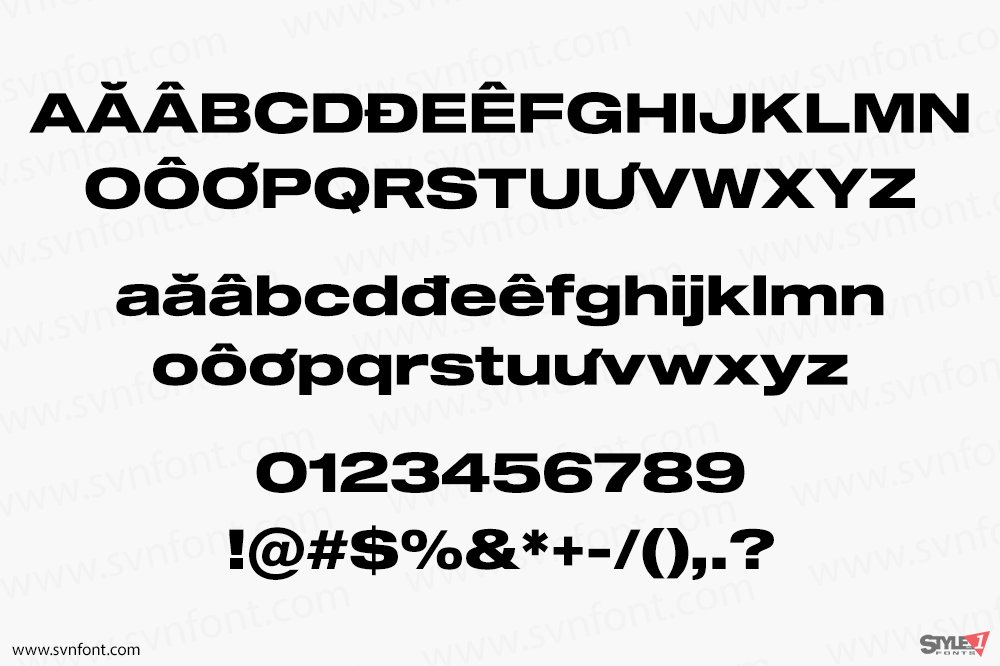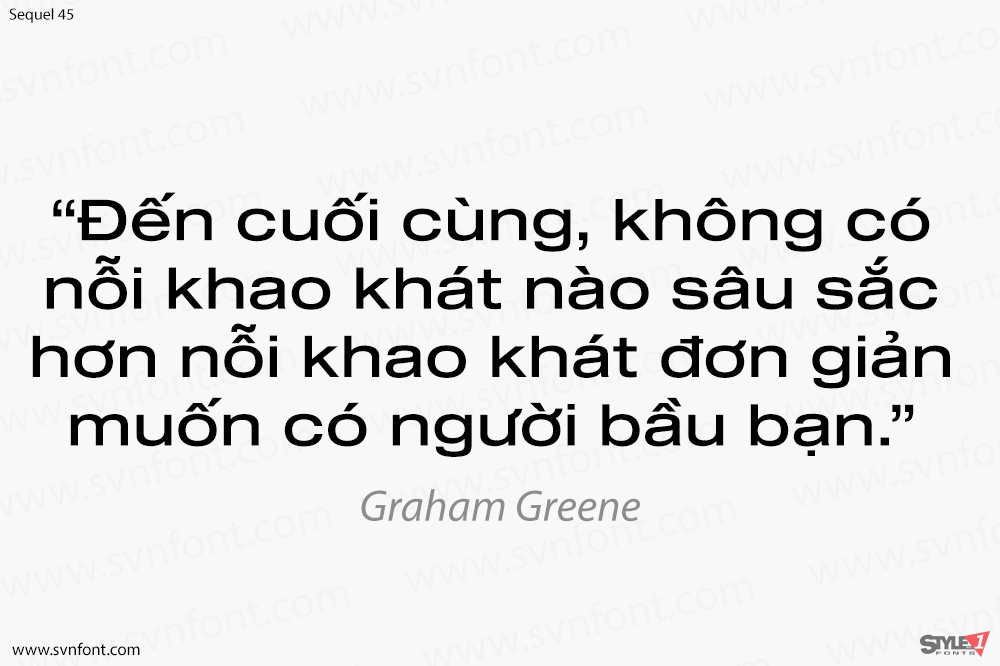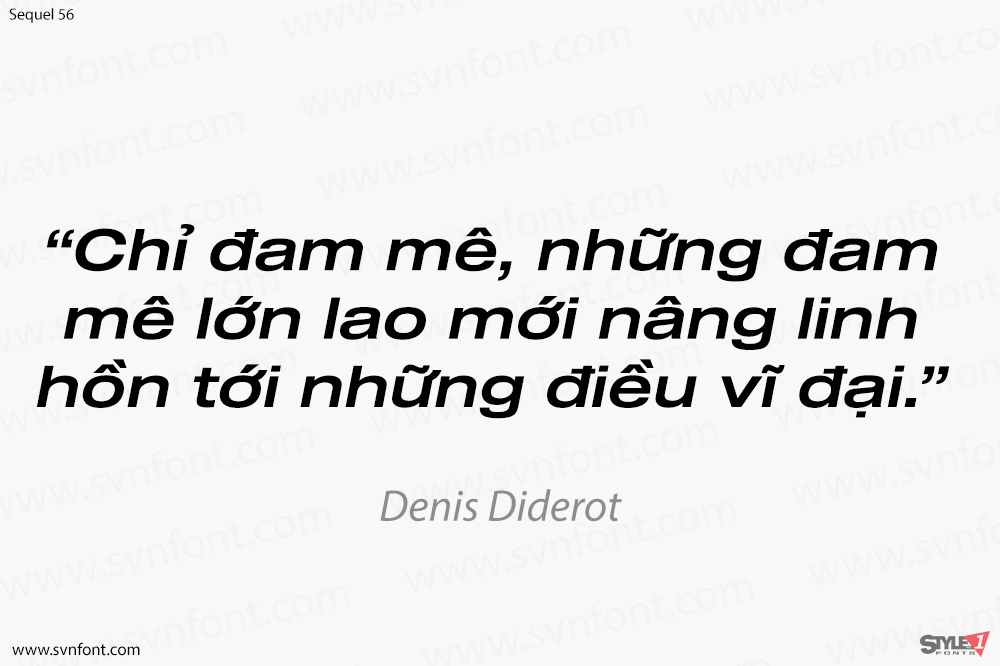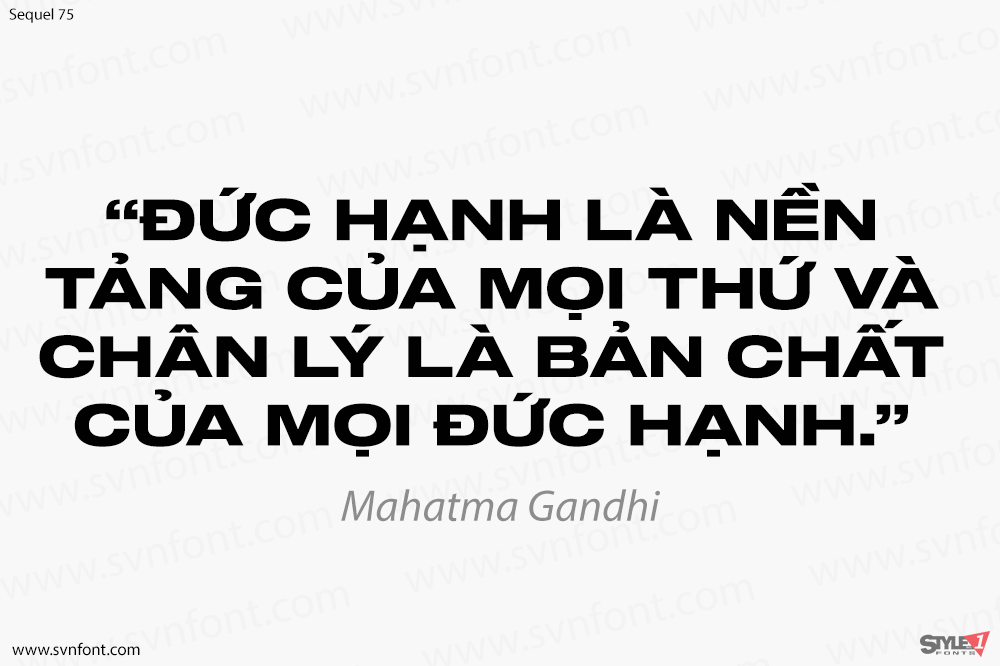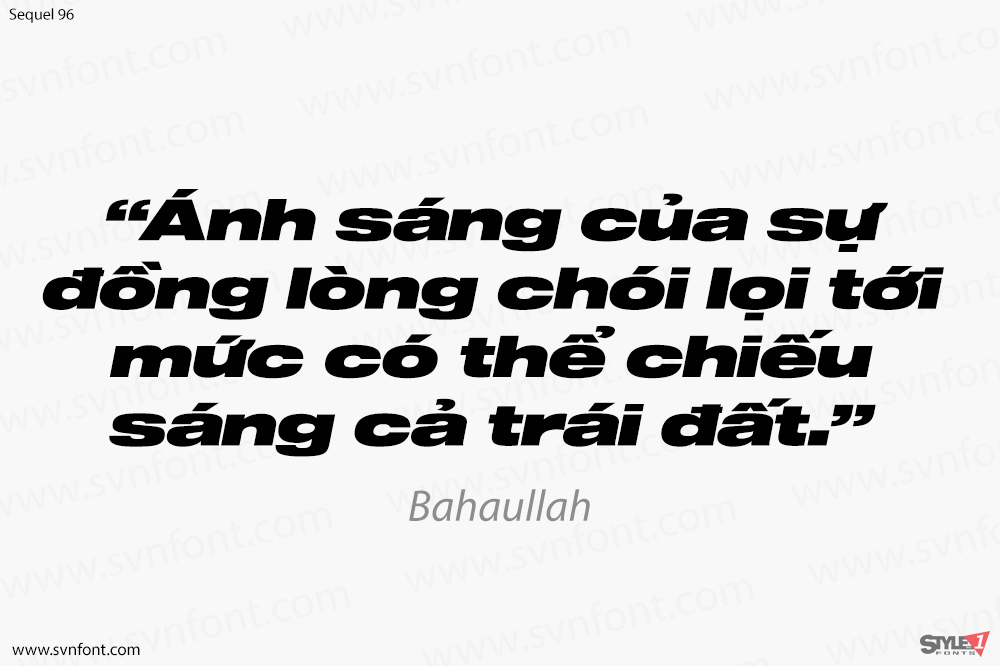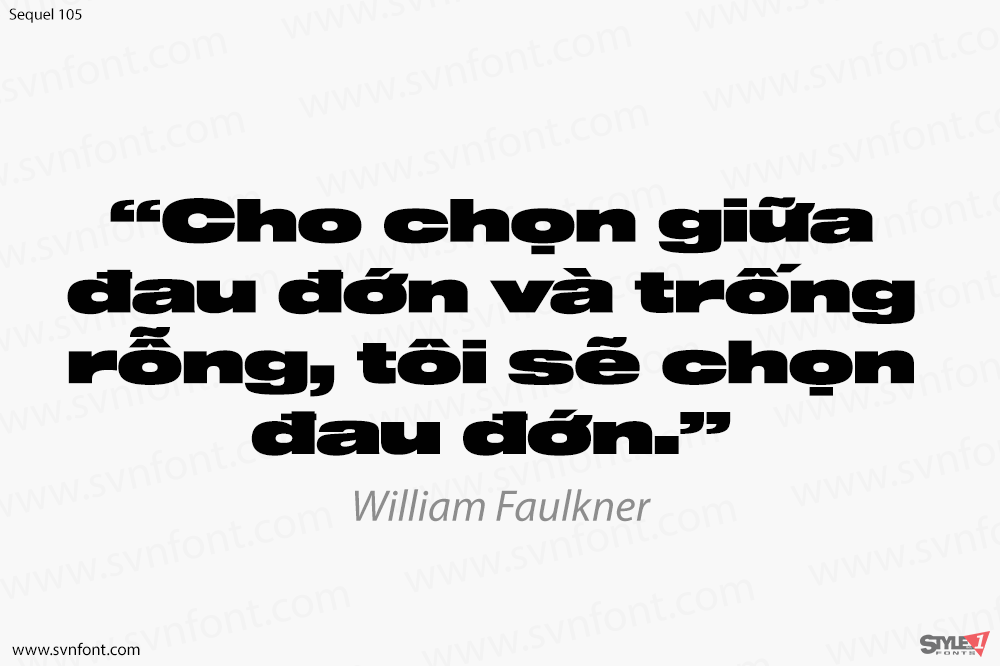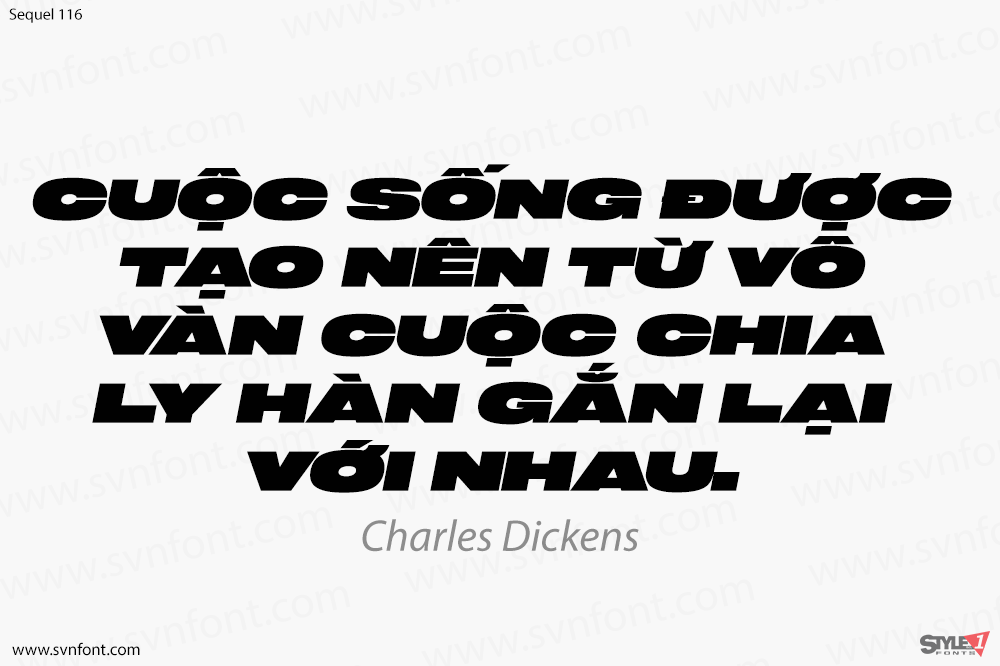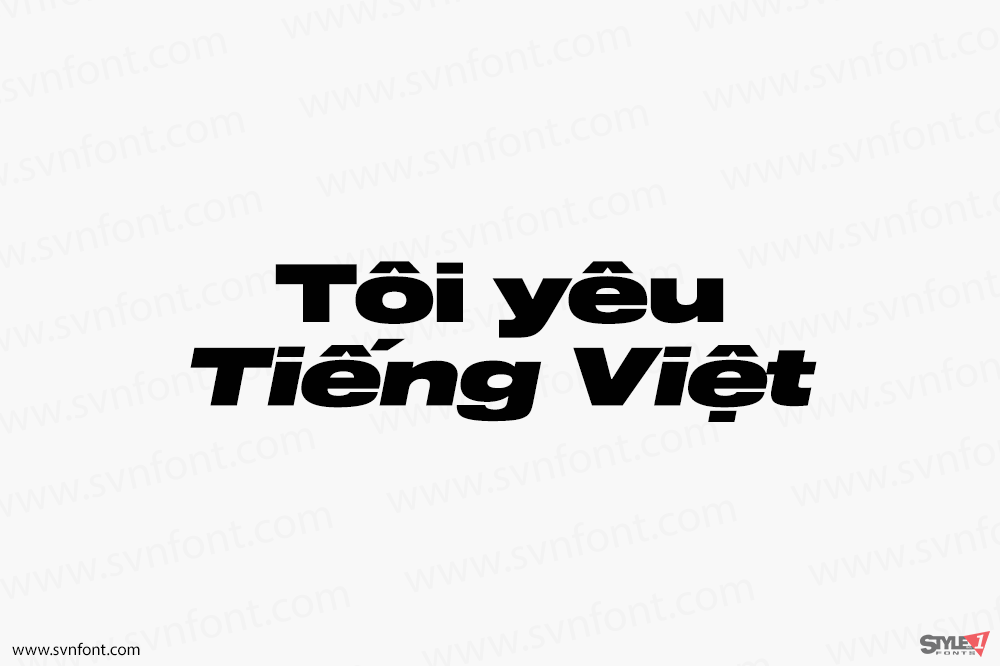
Sequel là một họ font neogrotesque dành cho các tiêu đề mạnh mẽ, các tựa đề tự tin và các áp phích ấn tượng. Là một phần mở rộng của Sequel Sans và chủ yếu được thiết kế để sử dụng hiển thị, nó có tỷ lệ rộng hơn so với kiểu chữ gốc. Nó cũng có chiều cao x-height lớn hơn cho phép tạo ra tác động tối đa trên trang. Và Sequel 100 Black không hề nhẹ: nó là thành viên đậm nhất của đại họ Sequel, với độ đậm bắt đầu từ 45 (một kiểu trung bình chắc chắn) và lên đến mức cực đậm 115. Hãy sử dụng Sequel 100 Black bất cứ khi nào bạn muốn kết hợp một chút chủ nghĩa hiện đại giữa thế kỷ mát mẻ với sự căng thẳng lấp lánh của việc sử dụng mực tối đa và khoảng trắng tối thiểu.
Nhà thiết kế: Oliver Jeschke
Nhà phát hành: OGJ Type Design